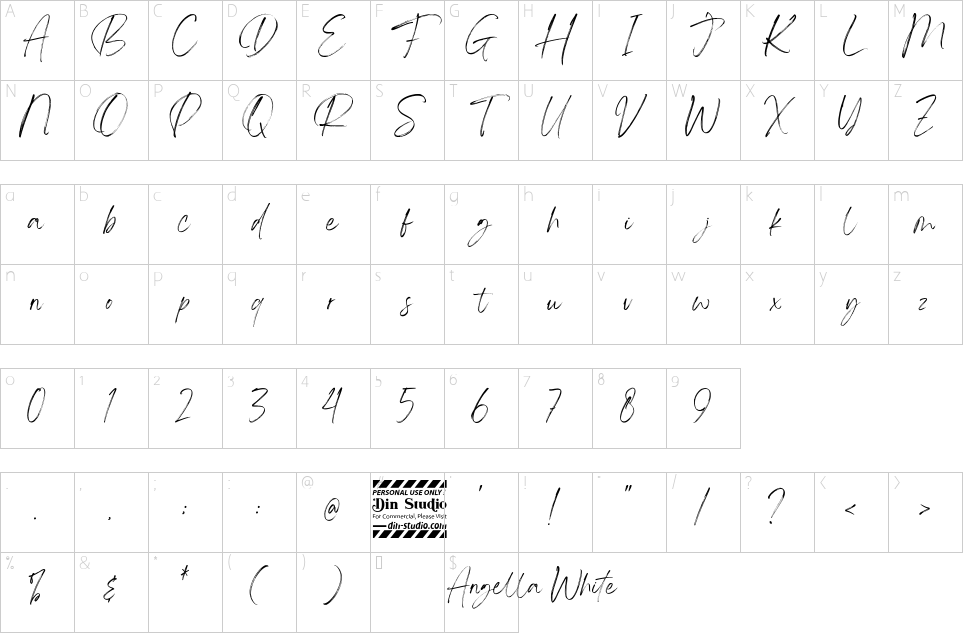
Angella White Font
A Angella White é uma fonte elegante e delicada, perfeitamente adaptada para aplicativos de escrita e design gráfico. Desenhada pelo designer Donis Miftahudin, esta fonte oferece um tom suave e harmonioso, que combina bem com diversos estilos de design, desde gráficos pessoais até elementos de design de aplicativos de alta qualidade. Com 492 usuários que já adquiriram e experimentaram a fonte, é claro que a Angella White atende a uma demanda crescente por fontes de qualidade. Se você está procurando por um elemento gráfico de alto nível para seus projetos, a Angella White é uma excelente escolha. Download grátis e encontre o design perfeito para seu próximo projeto.